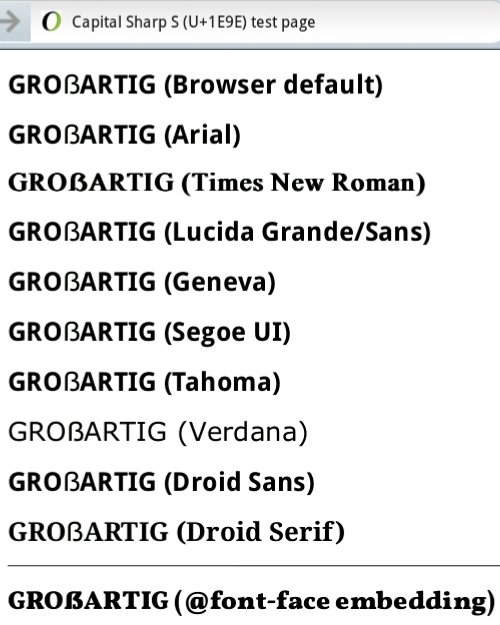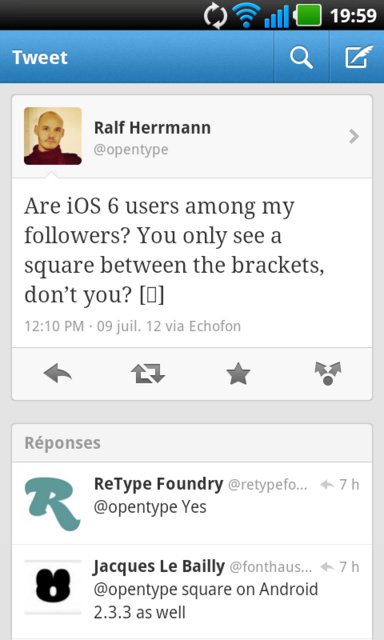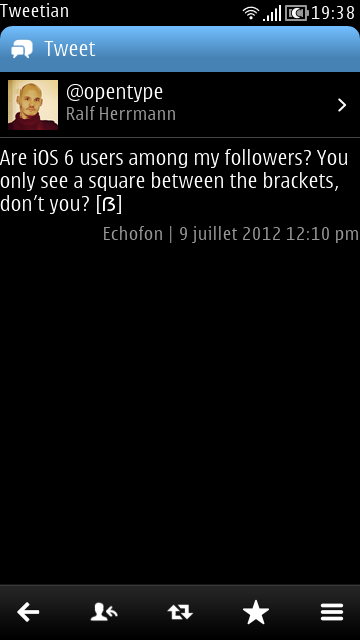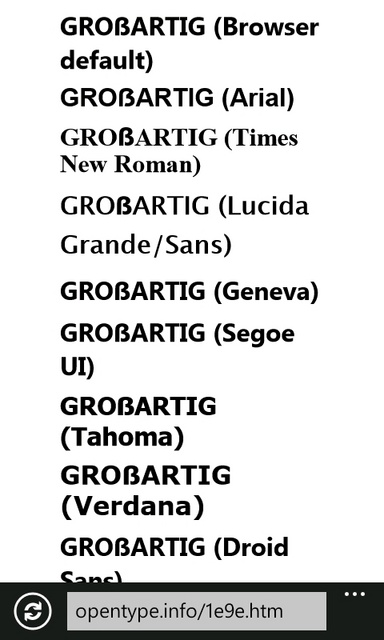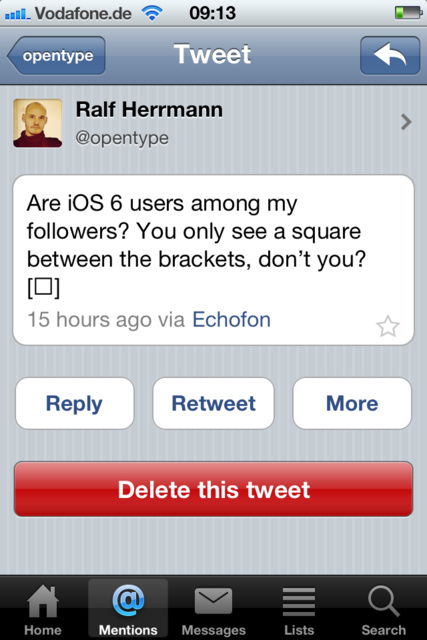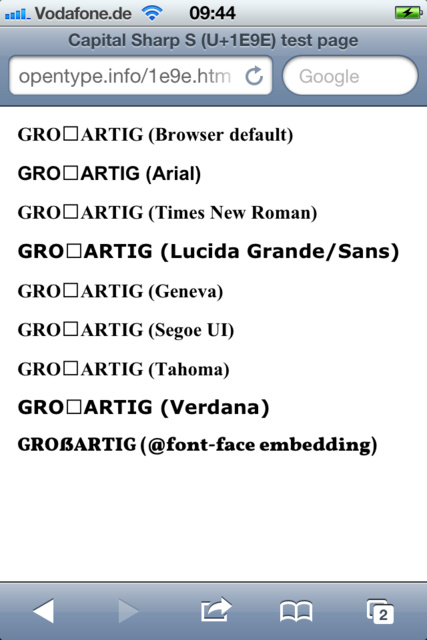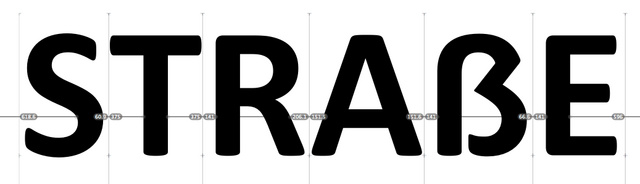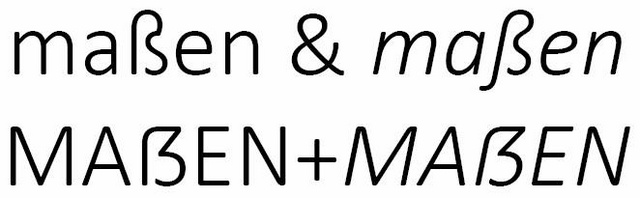
Versal-Eszett auf Smartphones und Tablets
Keine Unterstützung bei … Android
Ne, das stimmt spätestens ab Android 3.2 (Honeycomb) zum Glück nicht mehr.
Ich sehe auf meinem Honeycomb-Tablet auf deiner Testseite überall ein ẞ. Anscheinend bringen die Systemfonts zwei mit: ein serifiges, das in der 2. Zeile gezeigt wird (TNR) und ein serifenloses überall sonst über dem Trennstrich. Das serifenlose ist in den per <h1> standardmäßig fett gestellten Zeilen überall zu mager, aber wenigstens gibt es keinen leeren Rahmen.
(Das eingetettete Vollkorn-ẞ wird natürlich auch korrekt angezeigt.)
ich habe auch nur android 2.3.5 und sehe nur das über @font-face eingebundene versal-ẞ.
die droid bringt leider kein versal-ß mit ab android 4.0 (ice cream sandwich) wird aber roboto als
systemschrift verwendet. ein mix aus helvetica und univers.
ich hab kein versal-ẞ gefunden, kann aber auch an mir liegen, vielleicht hat ja jemand lust
und zeit die glyphentabelle zu durchforsten:
Haben die Android-Geräte überhaupt den gleichen Satz Systemschriften oder kocht da nicht jeder Anbieter sein eigenes Süppchen?
Guter Punkt!¹ Droid Sans + Serif haben sie wohl alle, aber manche Hersteller/Vertreiber legen anscheinend noch (still und heimlich) ein paar Fonts dazu. Samsung hat es bei meinem Galaxy Tab 10.1 (nur WLAN; US-Version) anscheinend auch so gemacht. In den Menüeinstellungen sehe ich unter Screen Screen displaySet font → folgende Optionen:
1. Default font
2. Choco cooky
3. Helv Neue S
4. Rosemary
1. sieht nach der Droid Sans aus; 2. ist sehr helveticaartig; 3. und 4. sind Einzelbuchstabenhandschriften. Per HTML/CSS kann ich – bis auf die Default/Droid Sans – anscheinend keine dieser Schriften einbinden. Bei dieser Testseite sieht bis auf die Zeilen mit »font-family: serif« und »font-family: "Droid Serif"« alles gleich aus.
Stimmt, zumindest in der dort zu bekommenden Roboto Regular herrscht auf Position 1e9e gähnende Leere. :-(
… 4 Jahre nach der Unicode-Einführung wäre ein Support ja nicht gerade übereilt …
4 Jahre nach der Unicode-Einführung wäre ein Support ja nicht gerade übereilt …
Die Unicode-Einführung ist ja eine Sache. Der wirkliche Skandal ist, dass hier ein Buchstabe einer der wichtigsten EU-Sprachen ignoriert wird, der im Alltag regelmäßig benutzt wird. (Mein aktuelles Beispiel ist das neulich hier gezeigte RWE-Plakat: mainstreamiger und konservativer als von solch einem Konzerngiganten geht’s wohl kaum.)
Wenn man sich anguckt, was in aktuellen Systemschriften so kodiert ist, wird schnell klar, dass es eben nicht um die wichtigsten oder aktuell am meisten benutzten Zeichen geht, sondern anscheinend nur darum, was irgendwie immer schon bereit gestellt wurde und dann eben aus Tradition weiter mitgeschleppt wird. In der Roboto z.B. steckt so viel Schrapel, den nun wirklich kaum jemand auf Telefon oder Telefon vermissen würde, darunter eben jede Menge lange abgeschaffter Buchstaben. Speicherplatz oder Arbeitsaufwand ziehen jedenfalls nicht als Argumente gegen das ẞ! :bandit:
Die Ubuntu ist auch so ein Fall. Da steckt sonst was drin, aber kein ẞ. Wahrscheinlich, weil der bekennende ẞ/ß-Ablehner (und gebürtige Schweizer) Bruno Maag diesen Buchstaben eben – in welcher Form auch immer – für überflüssig hält. Und der zahlenden Kunde ist zu nett, um ihm diesbezüglich mal ordentlich auf die Füße zu treten. (Nachvollziehen lässt sich das gut in der ẞ-Diskussion im Ubuntu-Bug-Forum.) :bandit: :bandit:
Wahrscheinlich, weil der bekennende ẞ/ß-Ablehner (und gebürtige Schweizer) Bruno Maag diesen Buchstaben eben – in welcher Form auch immer – für überflüssig.
Ja, natürlich. Die Macht über die Implementierung liegt bei einigen wenigen Leuten bei den großen Software-/Hardware-Anbietern und den Schriftentwicklern die diese beauftragen.
Da kann man nur weiter den Buchstaben einfordern und demonstrativ benutzen.
Ne, das stimmt spätestens ab Android 3.2 (Honeycomb) zum Glück nicht mehr.
Ich sehe auf meinem Honeycomb-Tablet auf deiner Testseite überall ein ẞ.
das ist aber kein versal-ẞ was du da siehst. das sieht mir sehr nach default aus.
ralf, woher kommt dieser krüppel, auf was wird da zurückgegriffen?
das ist aber kein versal-ẞ was du da siehst.
Doch klar. Wenn der Code 1E9E angefordert wird, dann kommt die entsprechende Glyphe – es gibt kein Rückfallen auf ein ß.
Aber Microsoft hat ja anfangs alle seine ẞ sehr minuskelhaft gestaltet. Und genau so sieht das ẞ aus Torstens Screenshot auch aus.
Entgegen anders lautender Versprechungen sehe ich bei den bestehenden ẞ keine Verbesserungen.
Neu hinzugekommen ist ein ẞ in der Calibri (regular/italic/bold/bold italic). Das hat jedoch Ascender entworfen.
Lucas de Groot selbst hat für die neue Light-Schnitte ein eigenes gezeichnet:
In meinem Consumer Preview ist die noch nicht mit drin, aber in der finalen Version von Windows 8 dann wohl hoffentlich schon.